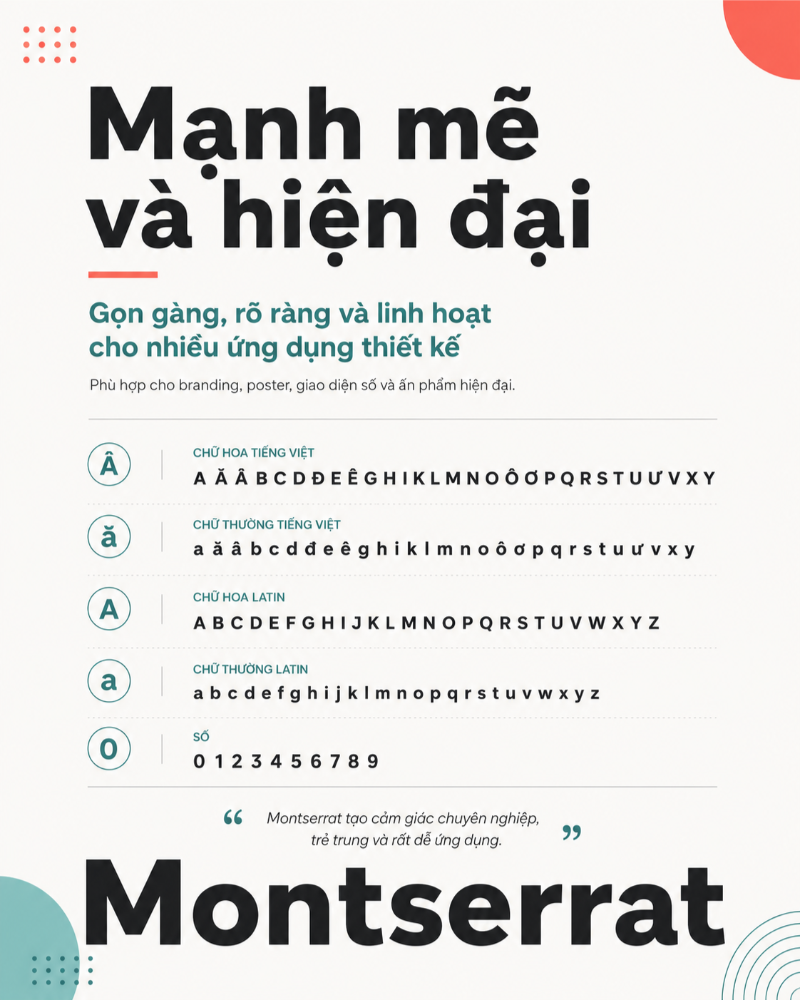
Một ấn phẩm thiết kế có thể sở hữu bố cục hoàn hảo, màu sắc hài hòa và hình ảnh sắc nét, nhưng chỉ cần một lỗi nhỏ ở font chữ tiếng Việt – như dấu ngã bị lệch, dấu hỏi sai tỷ lệ, hay font bị lỗi “ô vuông” – toàn bộ sự sang trọng sẽ sụp đổ trong nháy mắt. Đối với các Designer, việc tìm kiếm những bộ font vừa toát lên vẻ đẳng cấp, vừa hỗ trợ gõ tiếng Việt mượt mà luôn là một thử thách. Để bạn không phải mất nhiều thời gian tự tìm, tải và kiểm tra từng font, trong bài viết này, chúng tôi sẽ tổng hợp 15+ font chữ sang trọng đã được Việt hóa chỉn chu.
Vì sao font chữ ảnh hưởng trực tiếp đến cảm giác “sang trọng” của thiết kế?
Trong thiết kế đồ họa, font chữ không chỉ có nhiệm vụ truyền tải nội dung. Nó còn tạo cảm xúc, định hình phong cách và quyết định cách người xem cảm nhận về tổng thể thiết kế. Mỗi kiểu chữ, mỗi độ cong, độ dày mỏng hay khoảng cách giữa các ký tự đều mang một sắc thái riêng.
Các font chữ có chân thường tạo cảm giác cổ điển, quý phái và giàu tính nghệ thuật. Chúng phù hợp với những thiết kế cần thể hiện sự cao cấp, tinh tế hoặc mang hơi hướng di sản. Ngược lại, các font không chân với đường nét gọn gàng, tối giản lại mang đến cảm giác hiện đại, thanh lịch và chuyên nghiệp.
Tuy nhiên, một font chữ chỉ thật sự giữ được vẻ sang trọng khi hỗ trợ tiếng Việt chuẩn. Font Việt hóa tốt phải đảm bảo các dấu như hỏi, ngã, nặng, sắc, huyền được thiết kế đồng bộ với nét chữ gốc. Vị trí đặt dấu cần cân đối, không làm vỡ bố cục dòng chữ, không khiến khoảng cách dòng bị rối. Khi những chi tiết nhỏ này được xử lý chỉn chu, toàn bộ văn bản sẽ trở nên liền mạch, tinh tế và giữ đúng tinh thần cao cấp của thiết kế.
Top 15+ Font chữ sang trọng việt hóa, đẹp cho thiết kế
Để chọn đúng font cho từng dự án thiết kế, bạn không nên chỉ nhìn vào vẻ đẹp bề ngoài của chữ. Mỗi font chữ đều mang một tinh thần riêng, phù hợp với từng ngành hàng, phong cách thương hiệu và mục đích sử dụng khác nhau. Dưới đấy là các Font chữ việt hóa mà chúng tôi đã tổng hợp được, mời các bạn tham khảo:
SVN Magnificent
SVN Magnificent là một trong những font thể hiện rất rõ tinh thần tráng lệ và thanh lịch. Font sở hữu những đường cong mềm mại, kết hợp với nét thẳng chắc chắn, tạo nên cảm giác vừa uyển chuyển vừa mạnh mẽ. Khi dùng cho tiêu đề lớn, SVN Magnificent dễ tạo điểm nhấn sang trọng mà không bị quá phô trương.
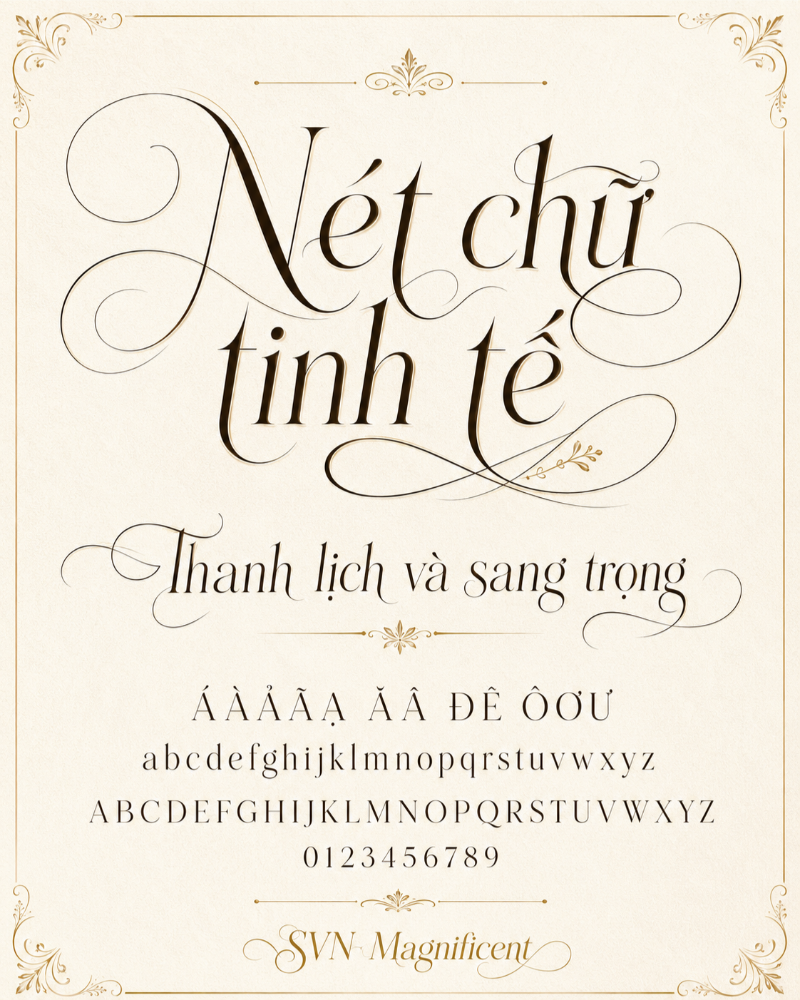
TH Buljirya
TH Buljirya mang đậm hơi thở cổ điển và quý phái của phong cách hoàng gia châu Âu. Các đường nét của font tạo cảm giác trang trọng, có chiều sâu và giàu tính di sản. Đây là lựa chọn đáng cân nhắc cho những thương hiệu muốn nhấn mạnh sự uy tín, lâu đời hoặc phong cách cao cấp mang màu sắc cổ điển.
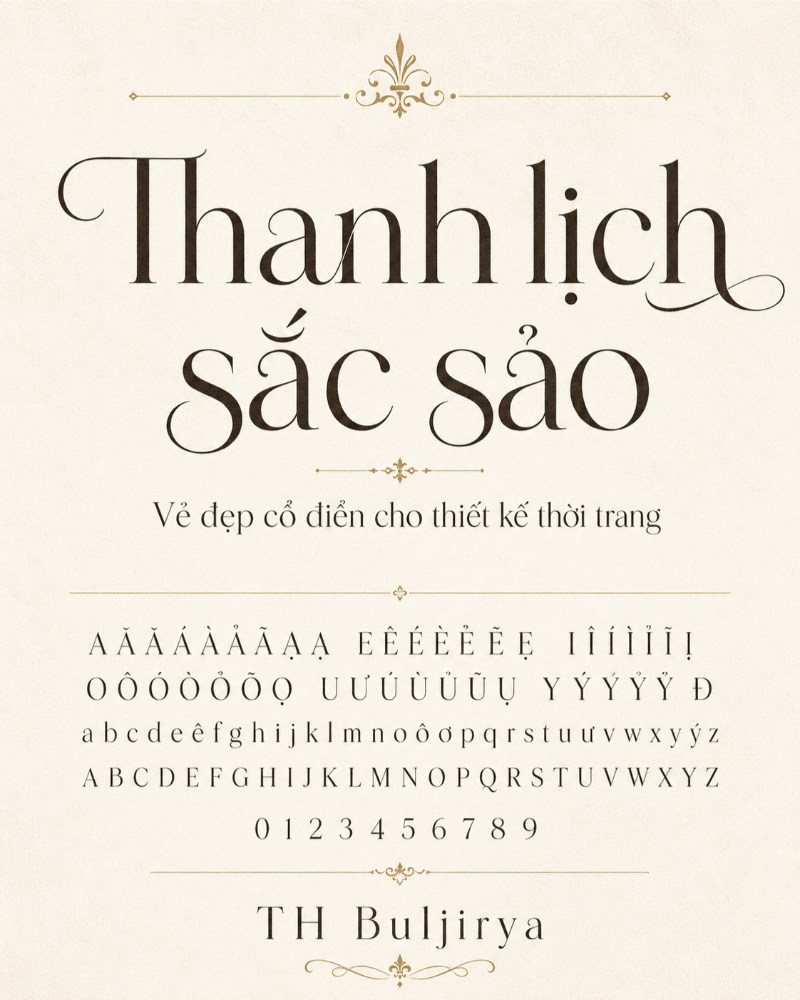
Playfair Display
Playfair Display bản Việt hóa là lựa chọn quen thuộc khi nhắc đến sự sang trọng hiện đại. Font có độ tương phản cao giữa nét dày và nét mỏng, giúp tiêu đề trở nên nổi bật, sắc nét và có sức hút thị giác mạnh. Playfair Display đặc biệt phù hợp với banner, poster, tiêu đề bài viết, lookbook thời trang và các thiết kế cần tạo cảm giác tinh tế ngay từ cái nhìn đầu tiên.
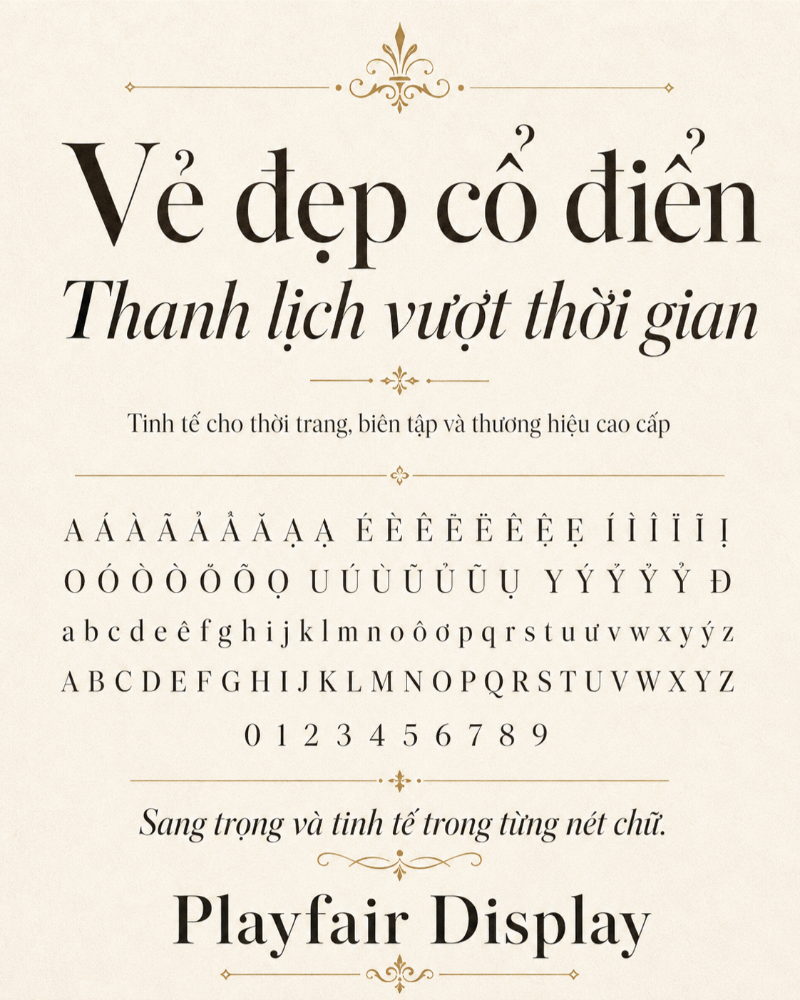
Bodoni hoặc SVN-Bodoni
Bodoni hoặc SVN-Bodoni lại mang vẻ đẹp sắc sảo, cá tính và có tính biểu tượng rất cao. Đây là dòng font thường xuất hiện trong các ấn phẩm thời trang cao cấp nhờ cấu trúc chữ thanh mảnh, góc cạnh và đầy khí chất. Nếu bạn muốn thiết kế có cảm giác giống bìa tạp chí thời trang, thương hiệu nước hoa hoặc chiến dịch quảng cáo xa xỉ, Bodoni là một lựa chọn rất đáng thử.
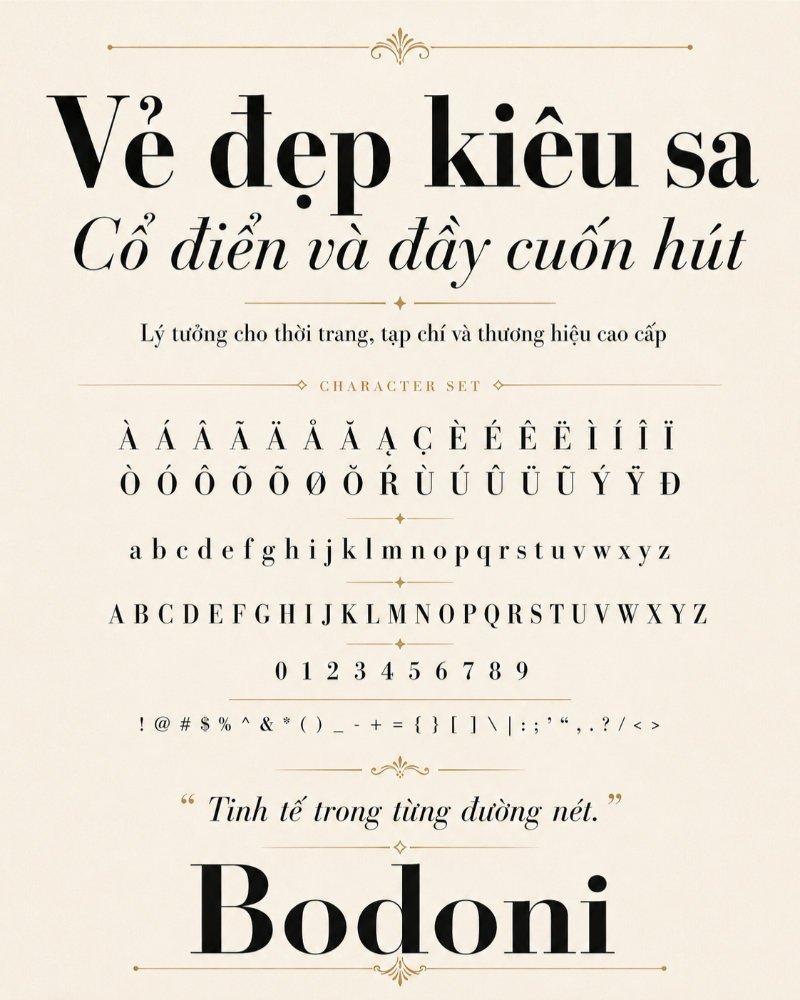
Merriweather
Merriweather có phần mềm mại và dễ đọc hơn so với Bodoni hay Playfair Display. Font này vẫn giữ được sự thanh lịch của nhóm Serif, nhưng không quá kịch tính hay cầu kỳ. Nhờ khả năng hiển thị tốt ở cả tiêu đề và nội dung dài, Merriweather phù hợp với website, bài blog, catalogue, hồ sơ thương hiệu hoặc các thiết kế cần giữ được sự trang nhã trong toàn bộ văn bản.
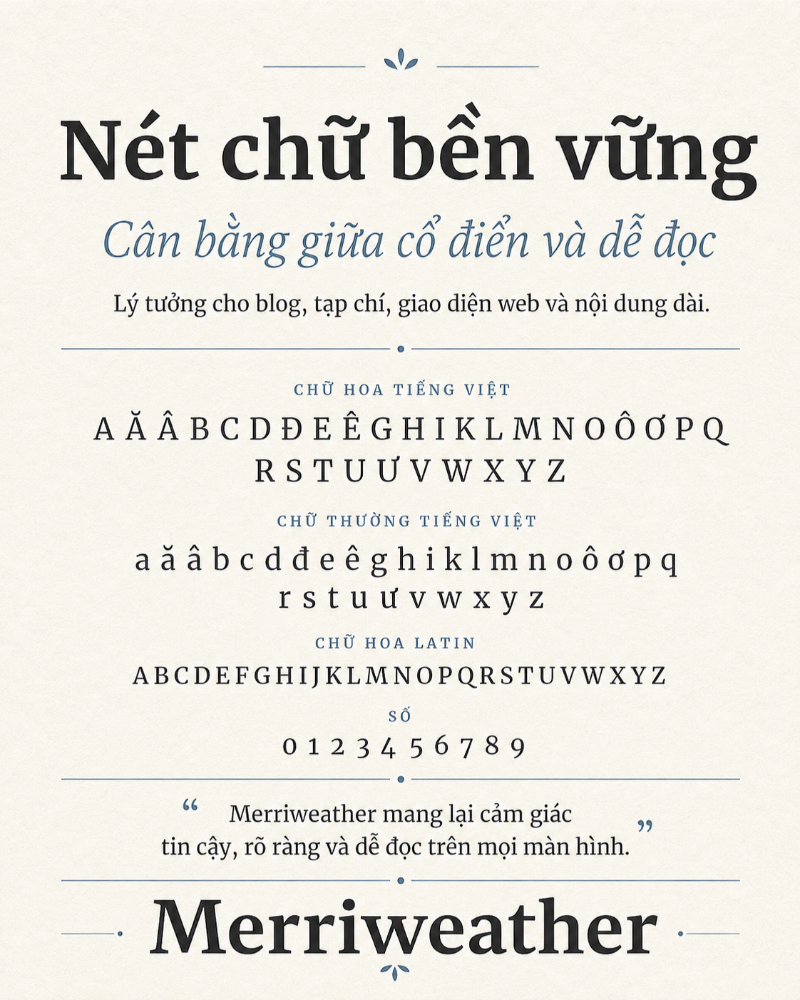
SVN Gilroy
SVN Gilroy nổi bật với cấu trúc hình học cân đối và hiện đại. Các nét chữ tròn trịa, sạch sẽ giúp font này tạo cảm giác thân thiện nhưng vẫn rất chuyên nghiệp. Gilroy đặc biệt phù hợp với các startup, thương hiệu trẻ, ứng dụng công nghệ hoặc những dự án cần hình ảnh năng động, chỉn chu và dễ ghi nhớ.
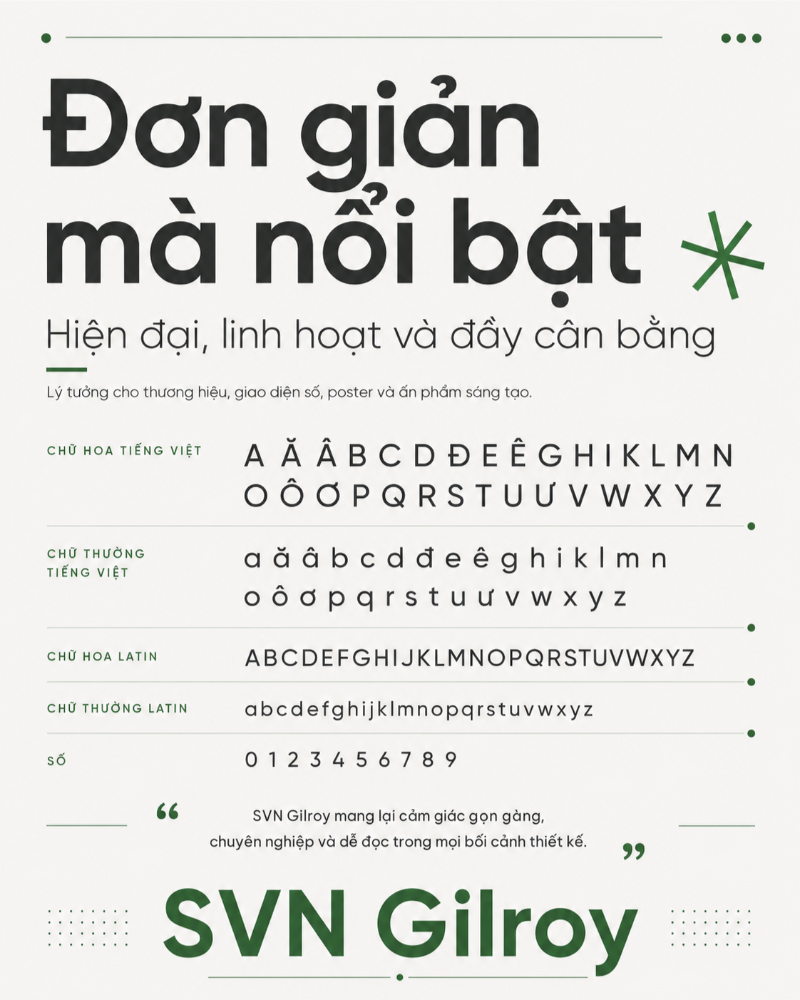
Metropolis
Metropolis mang vẻ ngoài vuông vức, chắc chắn nhưng không hề khô cứng. Font có những chi tiết bo góc tinh tế, giúp tổng thể chữ vừa vững chãi vừa mềm mại hơn khi hiển thị trên màn hình. Đây là lựa chọn an toàn cho thiết kế website, giao diện ứng dụng, banner số và các nội dung cần sự rõ ràng, ổn định.
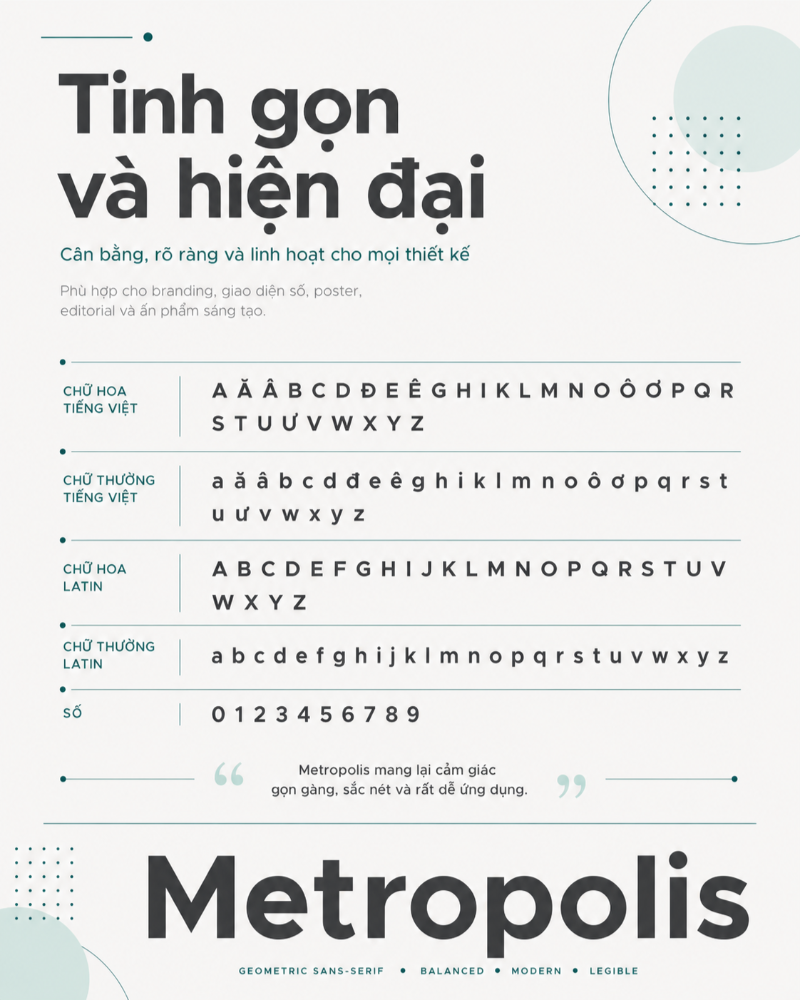
Cobe Sans
Cobe Sans mang tinh thần tối giản đặc trưng của phong cách Bắc Âu. Cấu trúc chữ gọn, thoáng và sạch giúp thiết kế trở nên nhẹ nhàng, tinh tế hơn. Font này rất hợp với các thương hiệu lifestyle, nội thất, thời trang tối giản, mỹ phẩm thiên nhiên hoặc những dự án cần cảm giác cao cấp nhưng không phô trương.
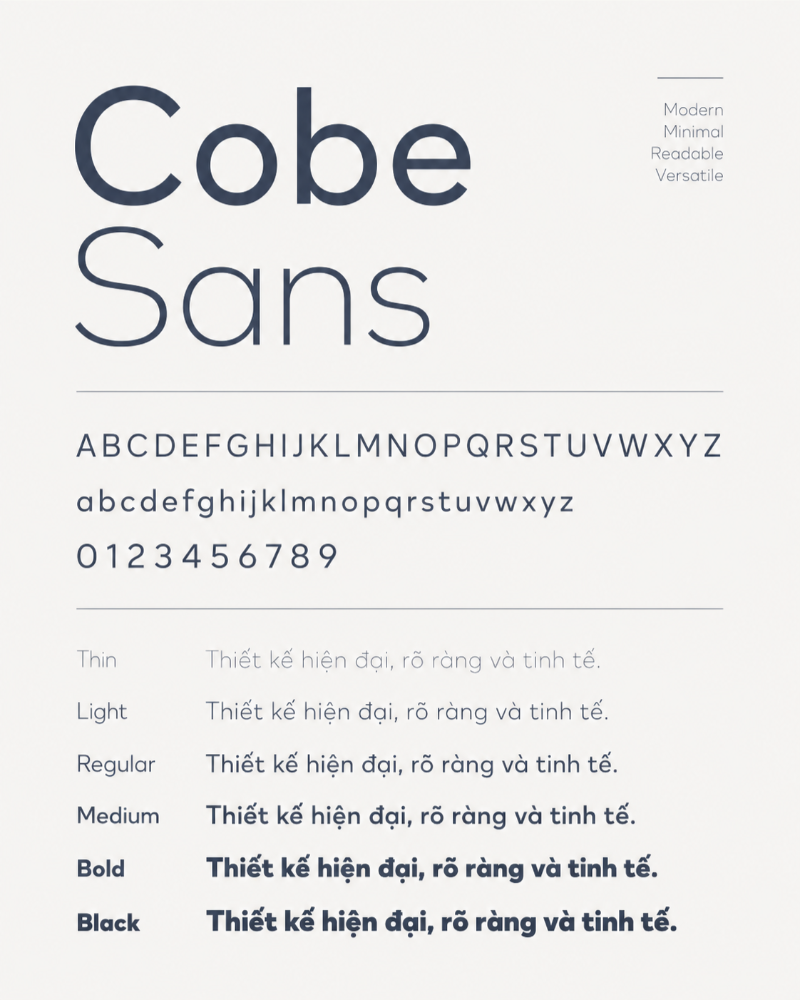
KD Boxroom
KD Boxroom là lựa chọn dành cho những thiết kế cần sự mạnh mẽ và nổi bật. Font có đường nét góc cạnh, dứt khoát và tạo cảm giác áp đảo ngay từ cái nhìn đầu tiên. Bạn nên dùng KD Boxroom cho headline, poster, banner quảng cáo hoặc các tiêu đề lớn cần thể hiện quyền lực, cá tính và sức hút thị giác mạnh.
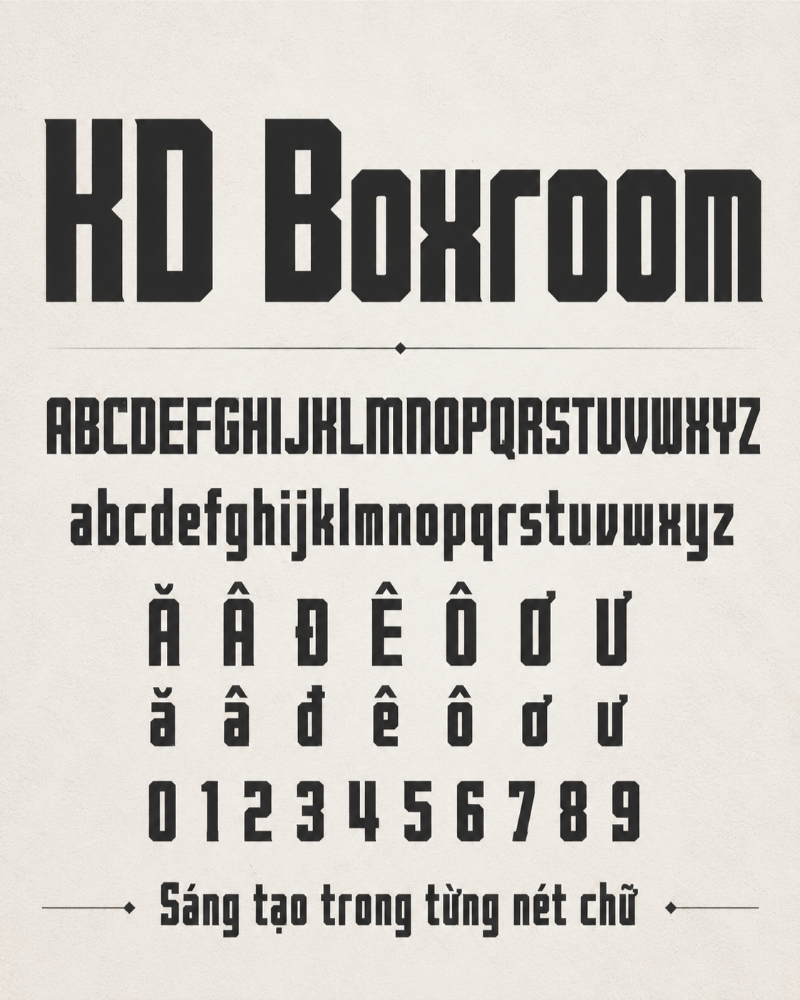
Một font chữ được chọn đúng có thể làm thay đổi cảm nhận về toàn bộ thiết kế. Nó giúp ấn phẩm trở nên tinh tế, chuyên nghiệp và có sức hút hơn thay vì chỉ dừng lại ở mức đẹp mắt thông thường. Hy vọng bộ sưu tập 15+ font chữ Việt hóa được chia sẻ trên đây sẽ giúp bạn có thêm ý tưởng và lựa chọn phù hợp cho những dự án thiết kế sắp tới.